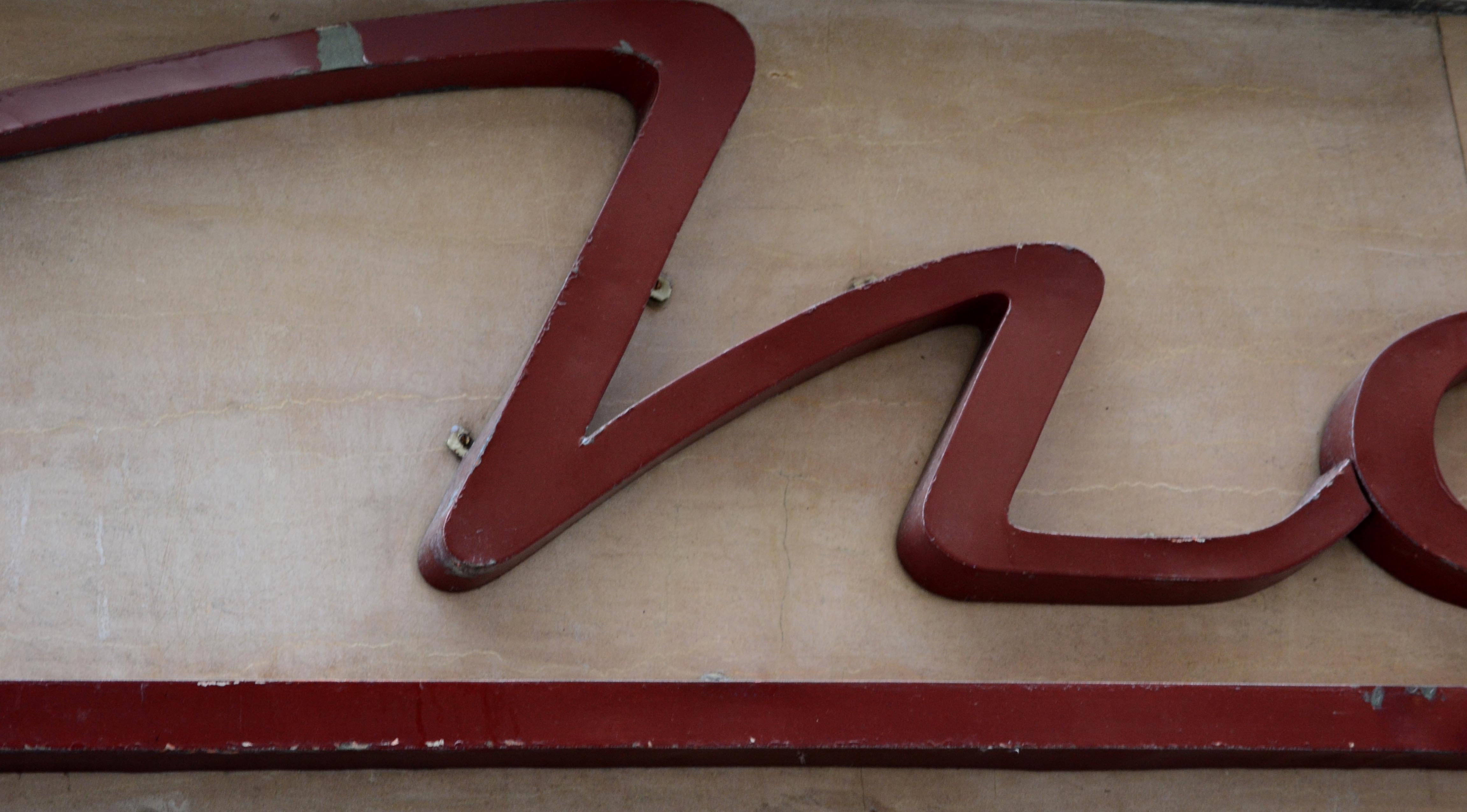
1932
[wyde_info_box title=»Tipografía» icon_set=»typicons» icon_typicons=»typcn typcn-sort-alphabetically»]Script[/wyde_info_box][wyde_info_box title=»Técnica» icon_set=»typicons» icon_typicons=»typcn typcn-brush»]Metal[/wyde_info_box]
Otro comercio que está a punto de llegar a la centena en Santander y que aún sigue abierto. Quizás lo que más llama la atención es su tipografía script; está inspirada en unas corbatas que se salvaron del incendio de 1941 y que asoló el centro de la ciudad, llevándose por delante tiendas que algunos casos desaparecieron para siempre y otros casos, como es este, tuvieron que buscar nuevas ubicaciones.